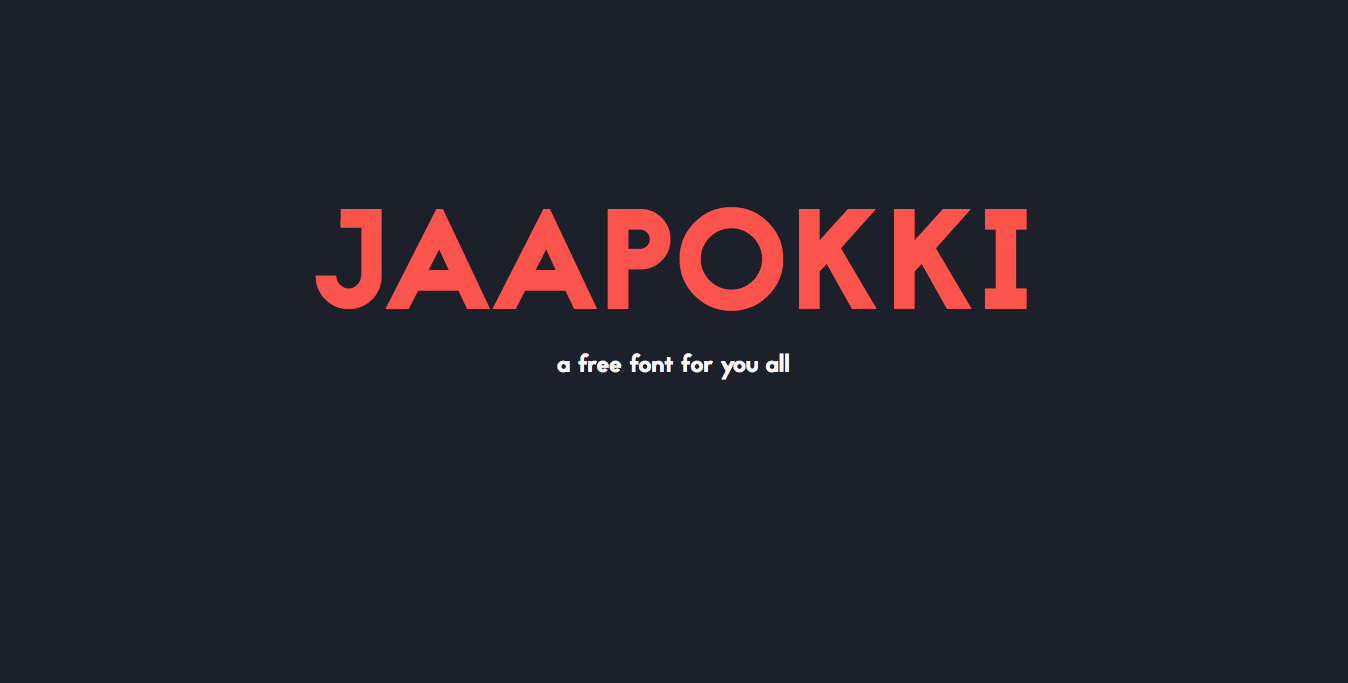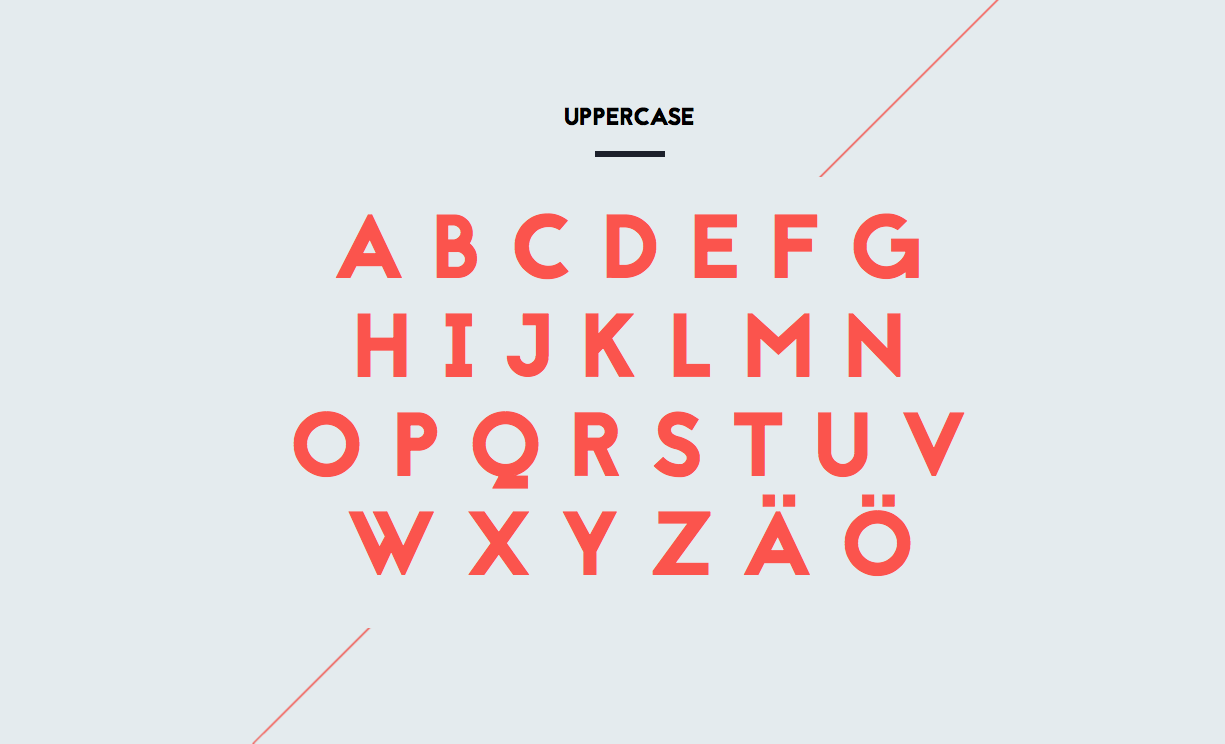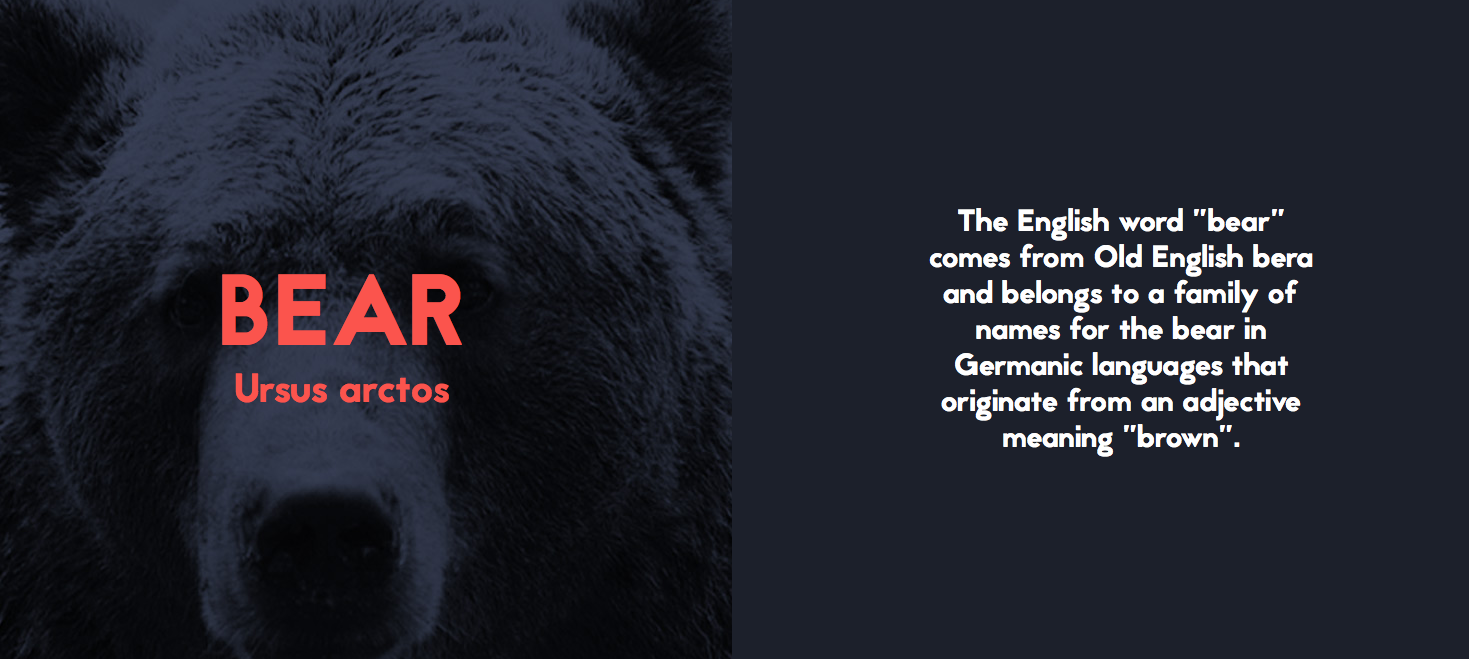
El diseñador gráfico finlandés Mikko Nuuttila nos obsequia con esta magnifica fuente tipográfica sans serif de uso totalmente gratuito para este monday font número 15. Jaapokki es un fuente limpia y bonita que nos salvará de apuros a la hora de diseñar ese proyecto “moderno” que llevas en mente.